Aún los negocios más áridos pueden tener buena publicidad… para muestra Lizzie Design.
Una casa de decoración no es árida — dirían muchos — y tal vez tengan razón, sin embargo les preguntaré ¿Cuándo fue la última vez que vieron publicidad llamativa para una de ellas? Replantearé la pregunta ¿Cuándo fue la primera vez que vieron una? Esperen, esperen… IKEA es mueblería también, de modo que no cuenta.
OK, una vez que hemos llegado al punto les comentaré que Lizzie Design es una empresa uruguaya que comercializa entre otras cosas, cortinas, persianas, toldos, cueros, papeles pintados… ¿papeles pintados? Sí, efectivamente… ¿Cómo vender papeles pintados de una manera llamativa? Suena a un reto ¿Verdad?
Pues bien, la solución de Lizzie Design fue el sueño de todo diseñador… ¡Con tipografía!
Esta fue la campaña que lanzó, con vistosos arreglos tipográficos y copys inteligentes, mostrando el producto de manera sencilla pero espectacular. Una sencilla pero vistosa dirección de arte para publicitar de manera creativa y contundente un producto cuya comercialización se antoja algo compleja. ¡El papel pintado de Manhattan está increíble!
Creative Directors: Pablo Alvarez, Guillermo Varela
Art Directors: Pablo Alvarez, Javier Venerio, Guillermo Varela, Natalia Maag, Miguel Corte
Copywriters: Pablo Alvarez, Samuel Liberman, German Kropman
Ilustration: Javier Venerio
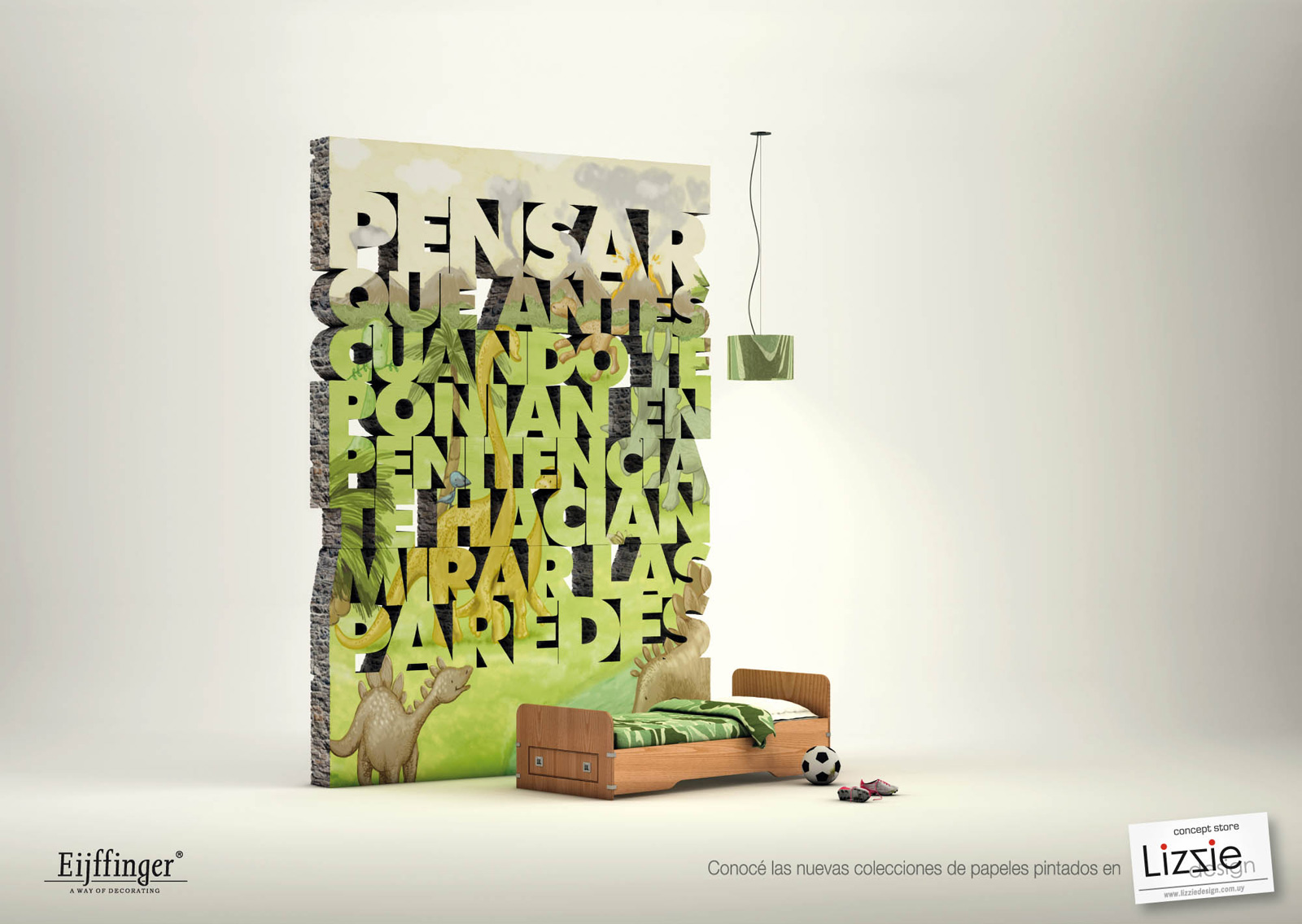
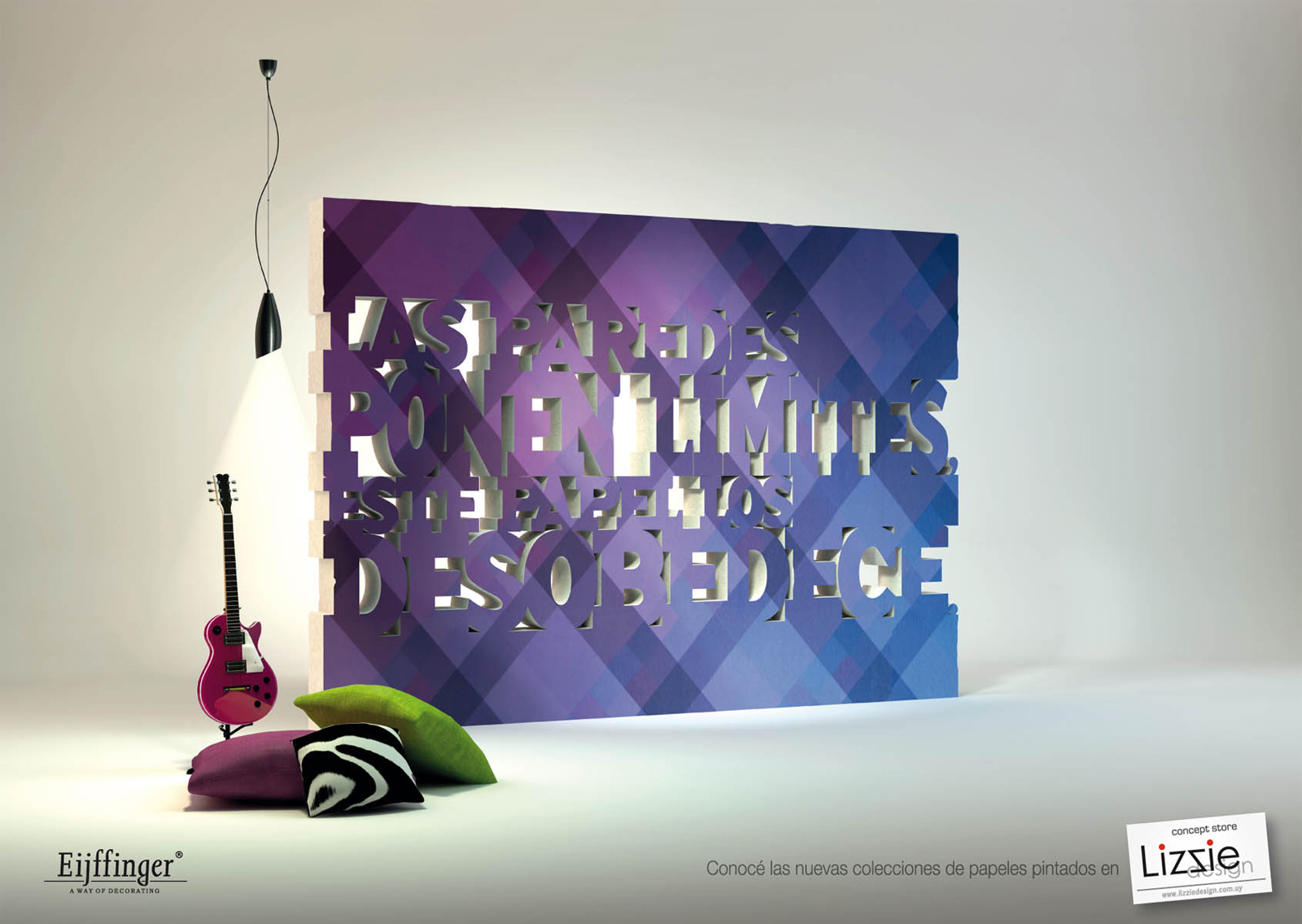
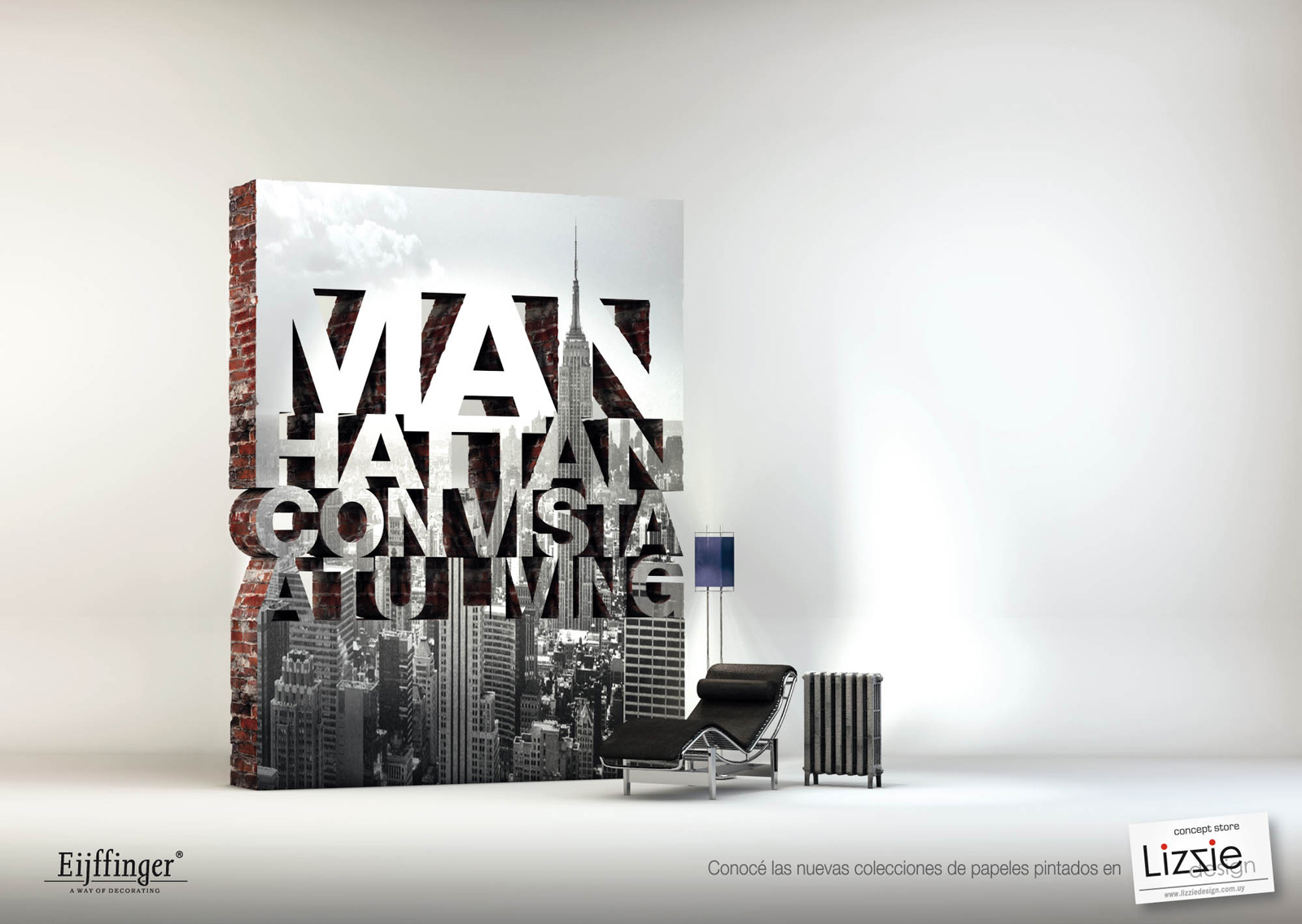
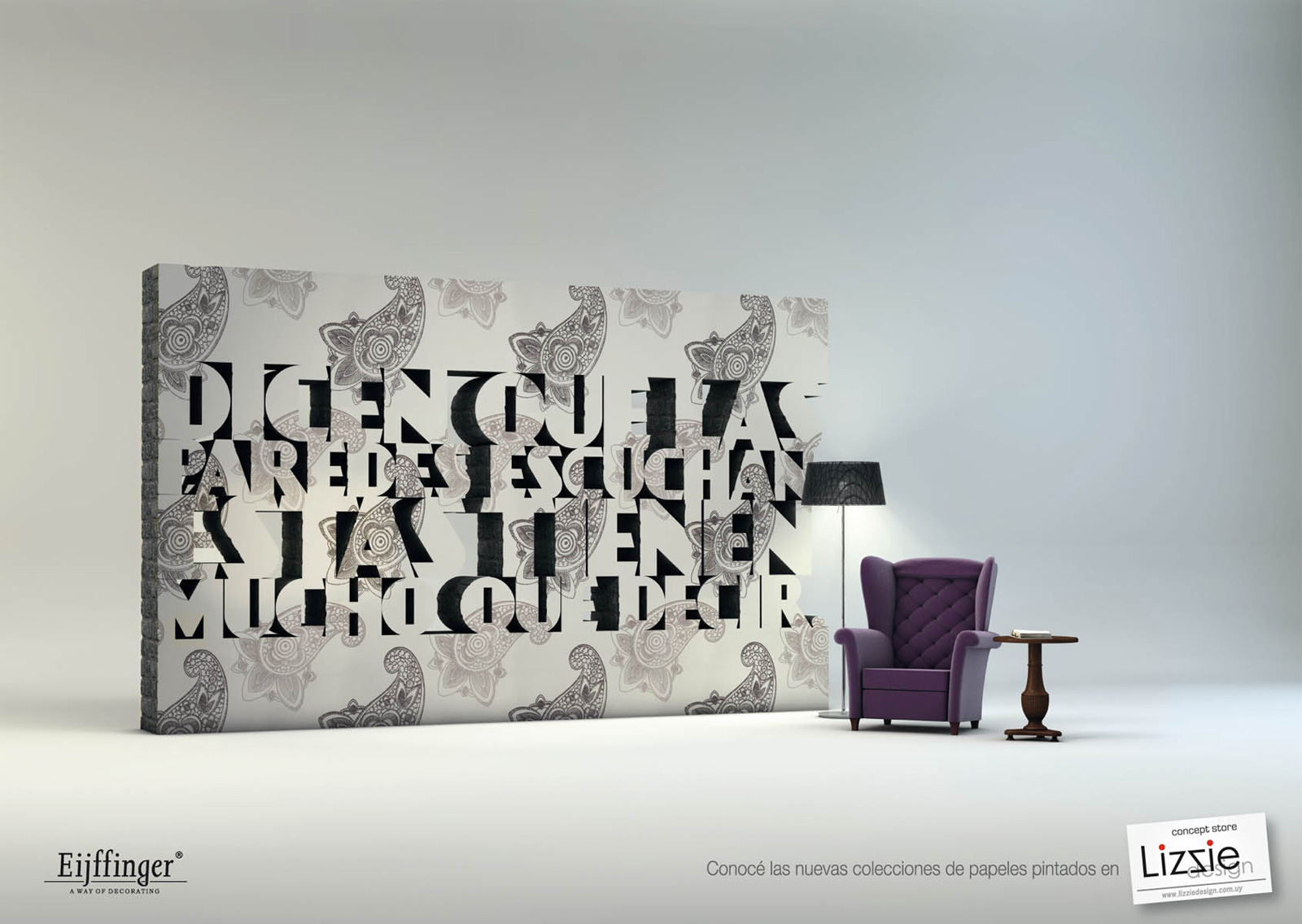
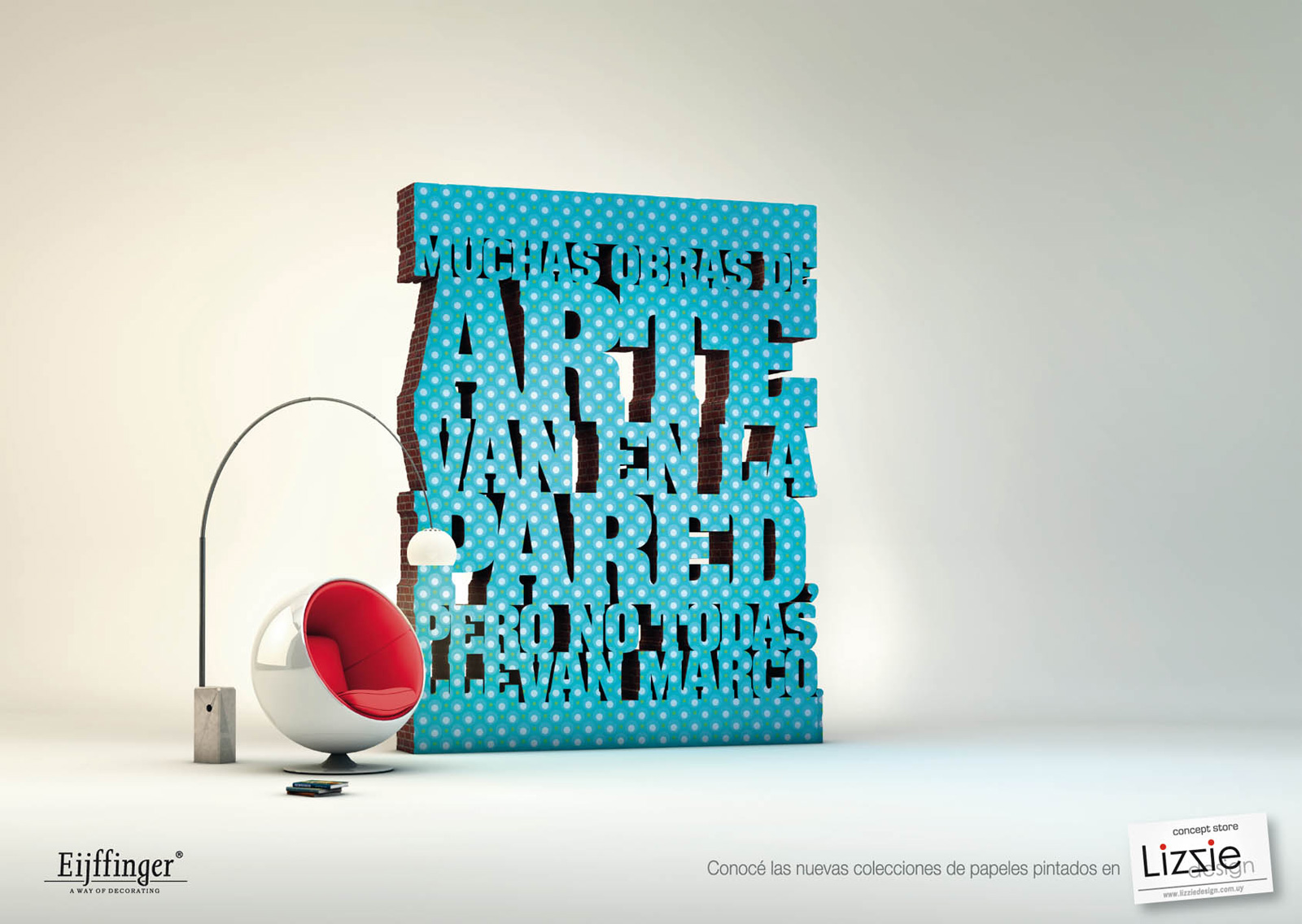
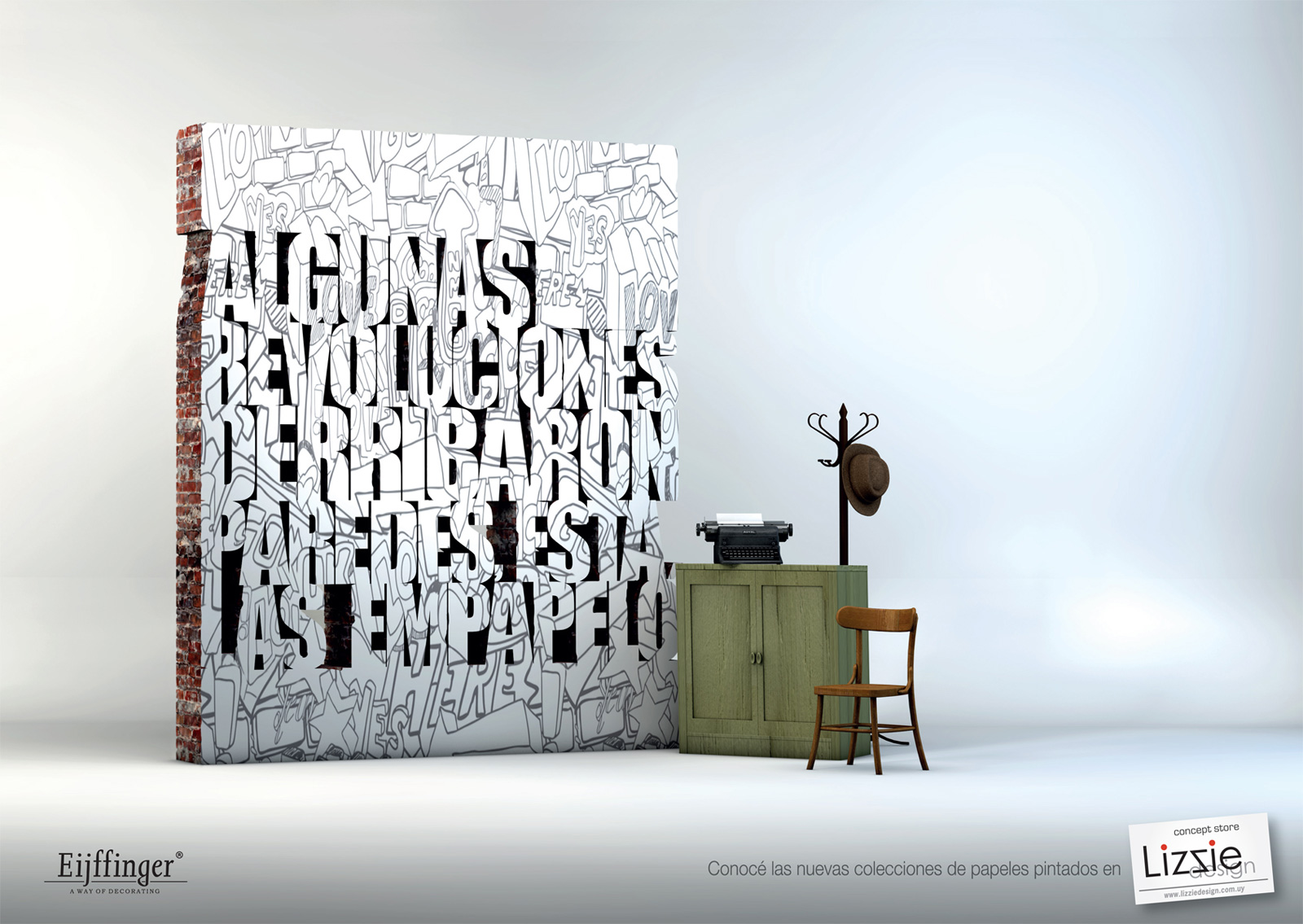
Qué buenas ideas; esta fue la frase, diseño y papel que más me gustó :)